基本書体セット
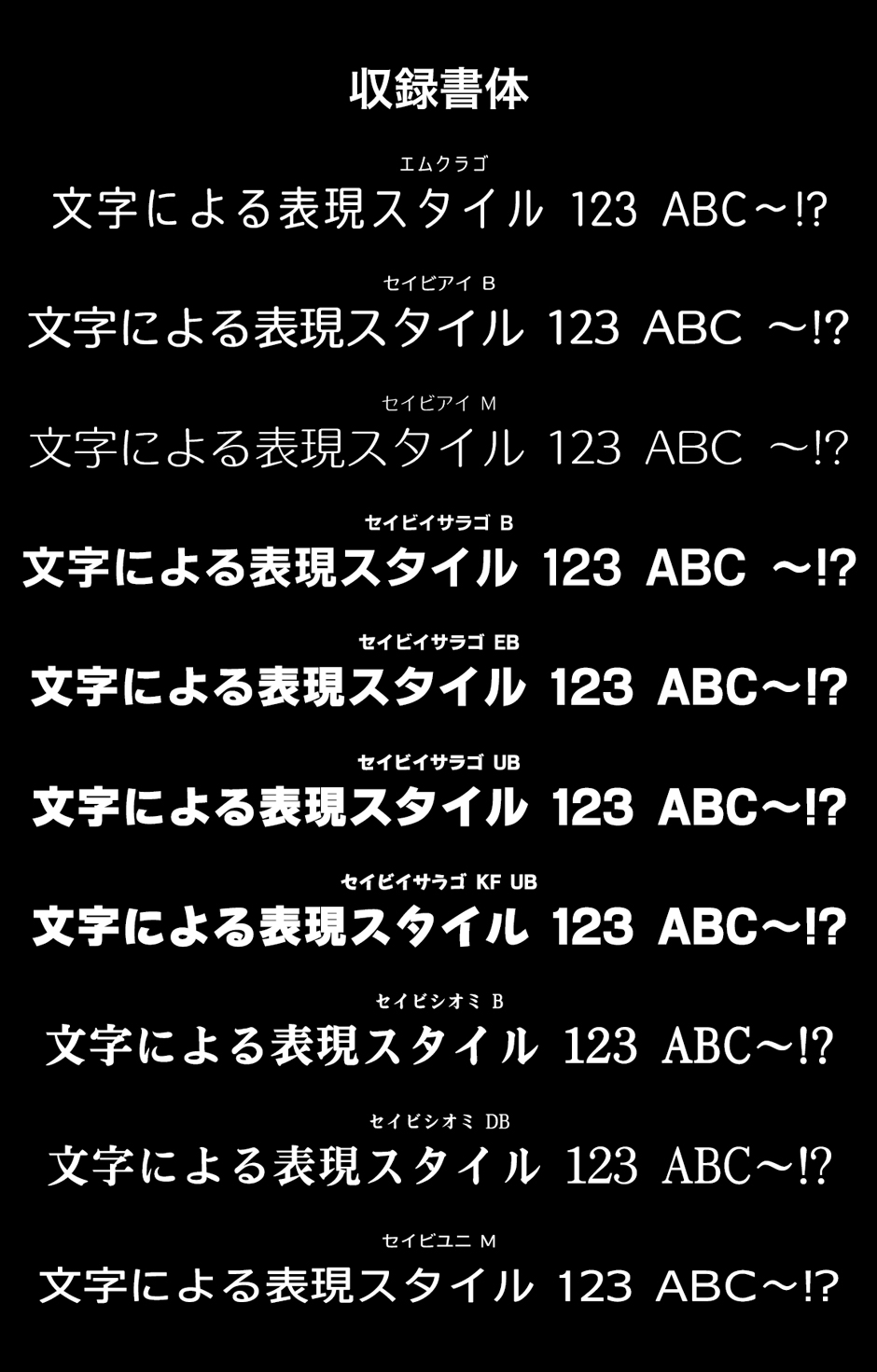
活字や写植にない書体、または既成の文字では表現できない書体がほしい、というお客様のご要望に応えて誕生した独自の書体ブランド「セイビフォント」。
この基本書体セットでは、このセイビフォントを中心に、可読性に優れた現代に使いやすいフォントをまとめております。
フトコロ(画と画の間の空間)を広くデザインした現代的感覚のゴシック体は、組み版時のライン揃えを考慮し、タテ組ヨコ組で違和感のないアップデートされた書体となっております。
小さな文字を白抜きで使用する場合などでもしっかり読みやすい明朝体や、角をややラウンドにし、ユニバーサルデザインを考慮した次世代ゴシック体など、まさに今すぐ使える贅沢なフォントを数多く揃えております。